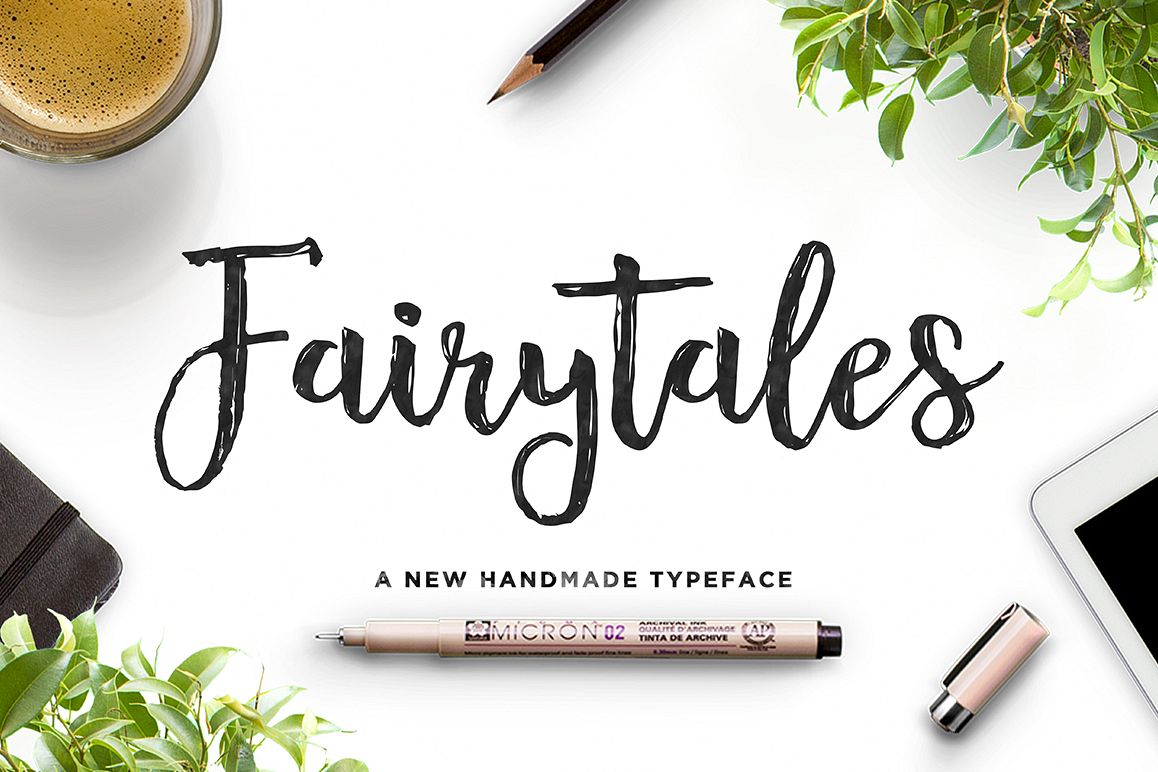
Fairytales Script
Fairytales Script adalah jenis huruf buatan tangan yang indah, garis dasar organik dan menari dengan berbagai swash yang dapat diterapkan pada awal dan akhir dari semua huruf kecil. Termasuk Huruf-huruf: Fairytales Script (OTF, TTF) Fairytales Script Swash (OTF, TTF) Termasuk dukungan internasional untuk sebagian besar Bahasa Barat. Untuk font swash yang terpisah, ketik huruf kecil az untuk swash awal dan akhir swash. Font ini dapat digunakan untuk berbagai keperluan. Seperti judul, tanda tangan, logo, undangan pernikahan, t-shirt, kop surat, signage, label, berita, poster, lencana, dll. Terima kasih banyak telah mencari dan beri tahu saya jika Anda memiliki ada pertanyaan.